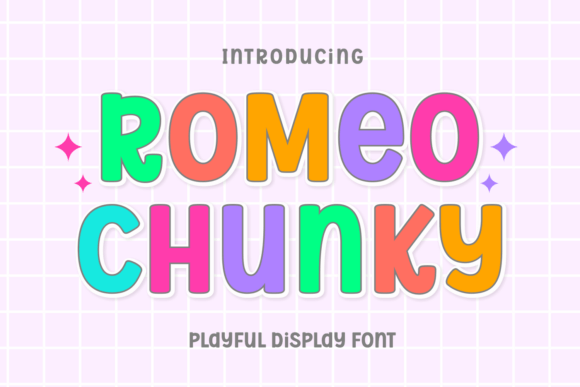
Romeo Chunky
適切なデザイン要素を見つけるのは難しい場合がありますが、Romeo Chunkyは作品を即座に引き立てる優れたコレクションを提供します。
POD(オンデマンド印刷)製品、結婚式の招待状、またはソーシャルメディアのグラフィックを作成している場合でも、Romeo Chunkyは理想的です。